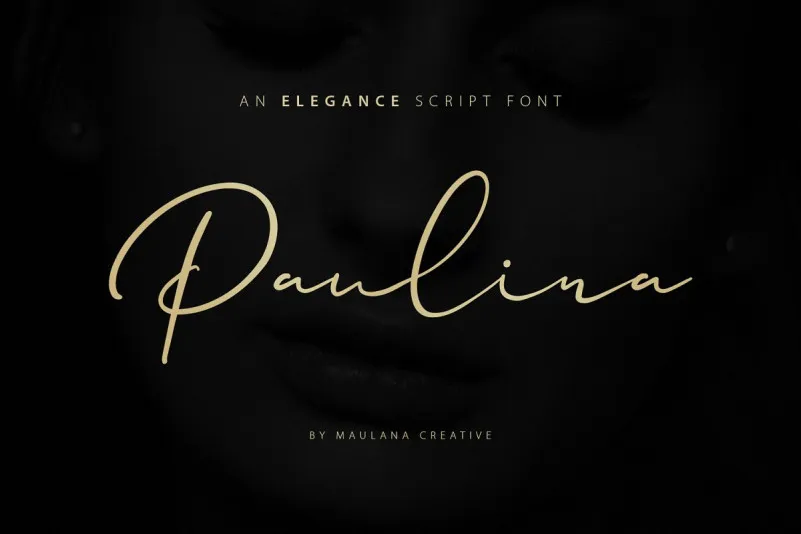
Paulina Elegance Script Font – Download Grátis
A Paulina Elegance Script Font é uma elegante seleção para os projetos mais sofisticados. Esta foi criada por M.0Type, e está disponível para compartilhamento pela Maulana Creative. Seja você um designer de gráficos ou simplesmente alguém que busca adicionar estilo à suas criações, a Paulina Script é perfeitamente adaptada para usar em diversas aplicações — desde assinaturas e logotipos até revistas e capas de livros. Suave e elegante, essa fonte escrita a mão se destaca como uma excelente opção para incorporar um toque autêntico e cuidadosamente feito à sua arte digital. Seja qual for o seu projeto, que seja ele assinatura, material de decoração ou criação de marca, a Paulina Elegance Script Font é perfeita para dar vida aos detalhes em qualquer design criado com ela.